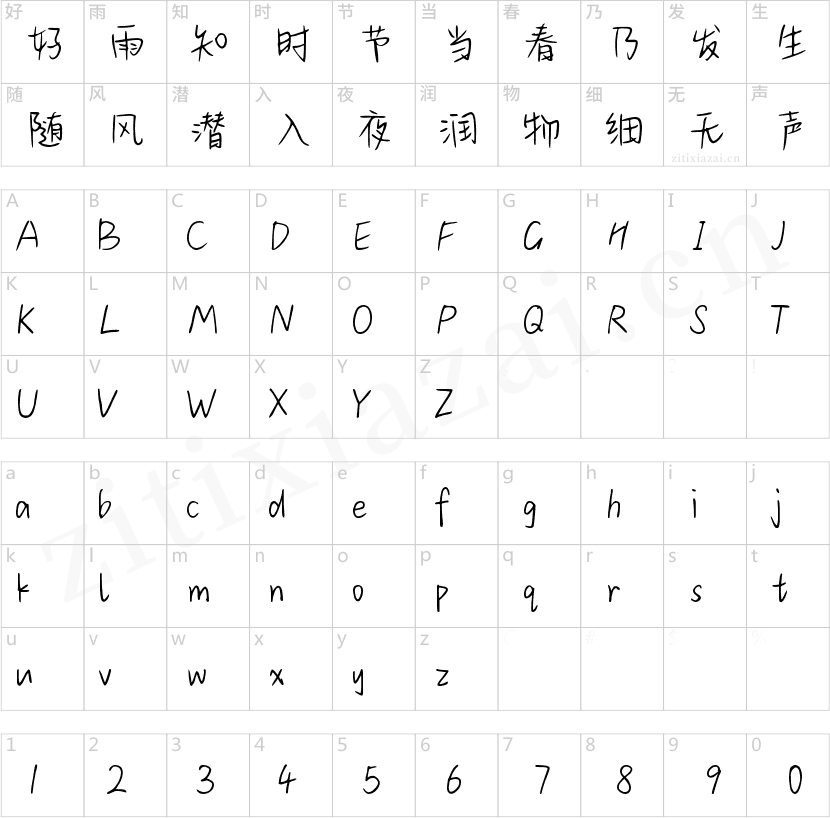
Aa做个气质小魔王
Aa做个气质小魔王字体
Aa做个气质小魔王是一款非常具有艺术性的字体,它的设计灵感来源于对古典艺术的研究,同时又融入了现代字体设计的元素。字形优美,笔画粗细变化自然,给人以大气、典雅的感觉。Aa做个气质小魔王是一款既传统又现代的字体,它的设计充满艺术感,美观大方,实用性也非常强。无论是对于设计师还是对于普通读者来说,都是一种非常不错的字体选择。Aa做个气质小魔王适合用于具有艺术感的场合,比如海报、宣传单张、书籍封面等。由于其字形流畅且具有动态感,也适合用于大量的文本排版,如报纸、杂志等。